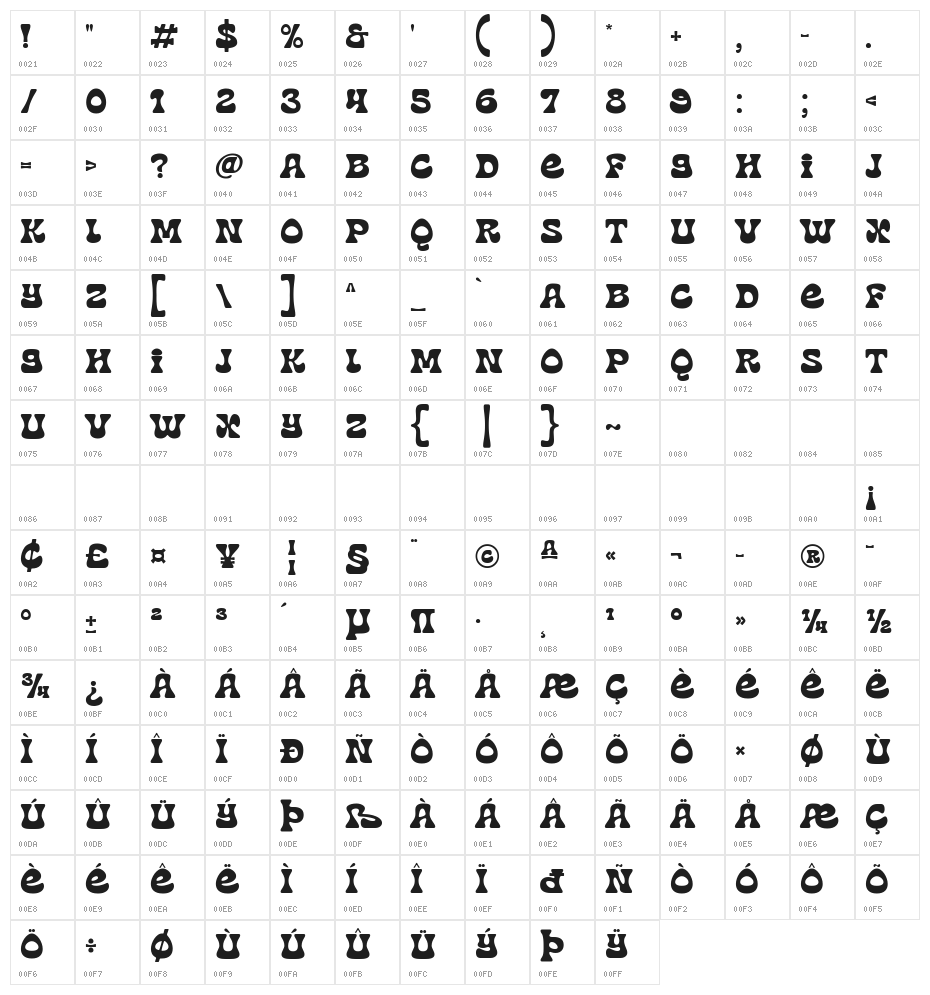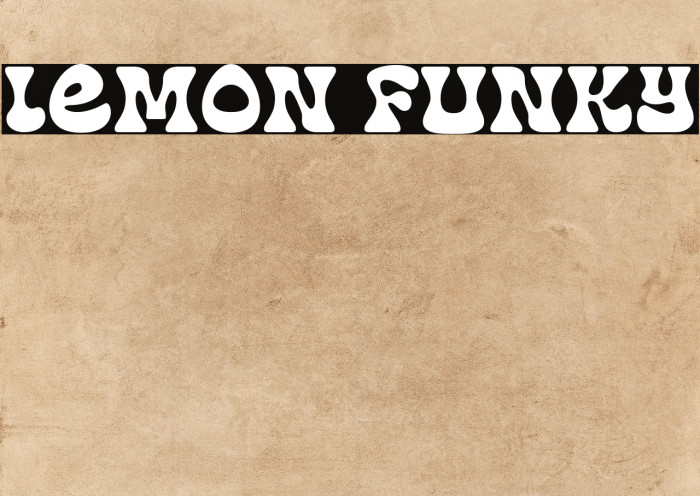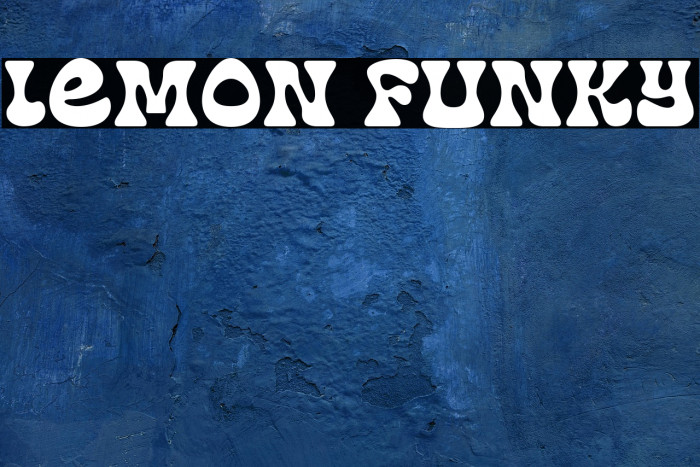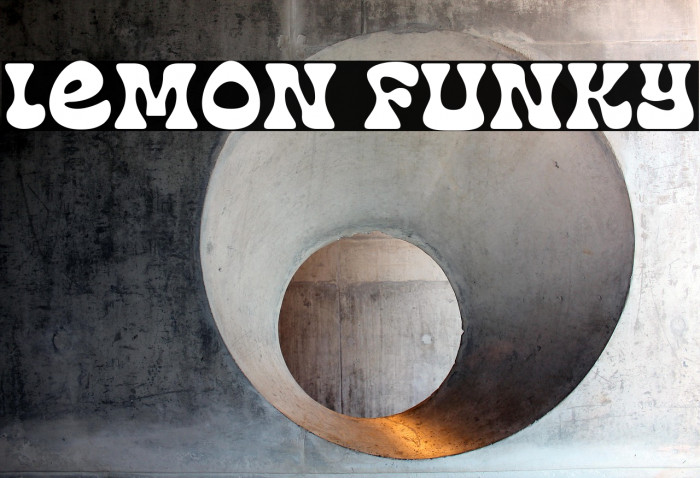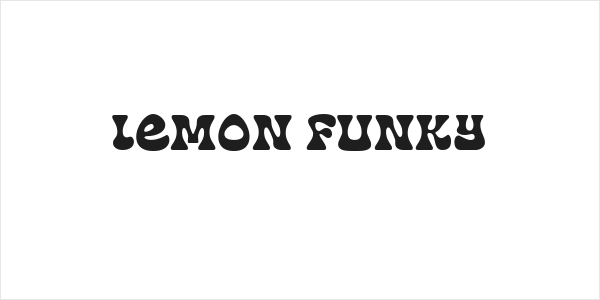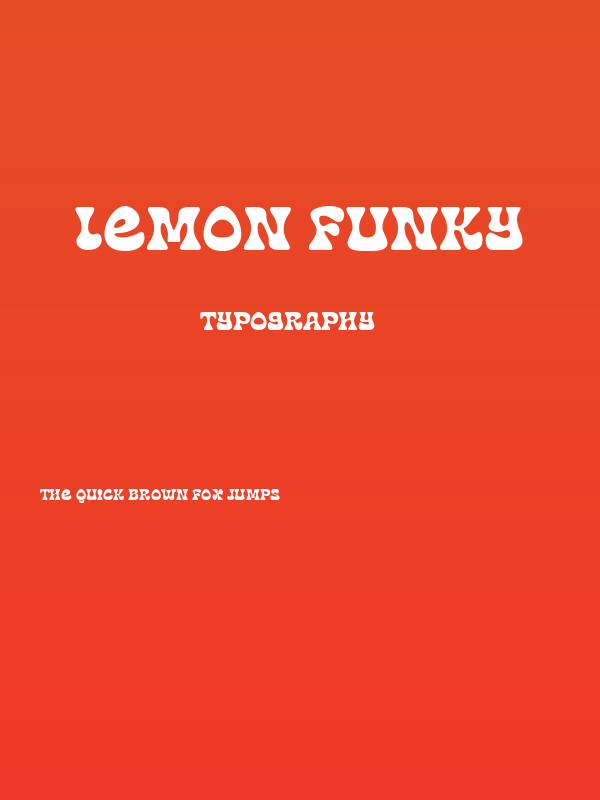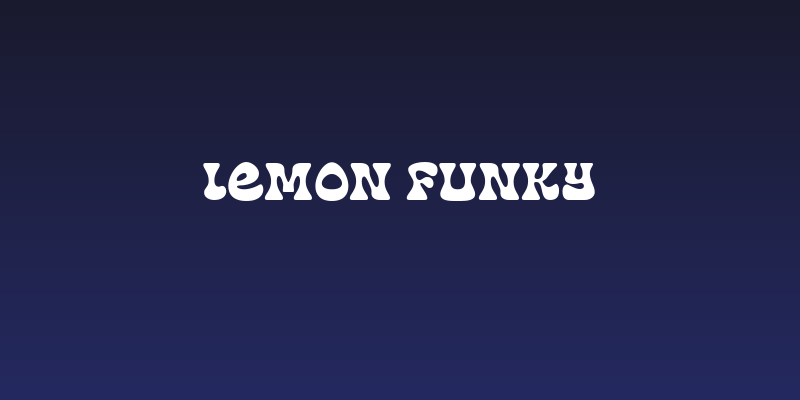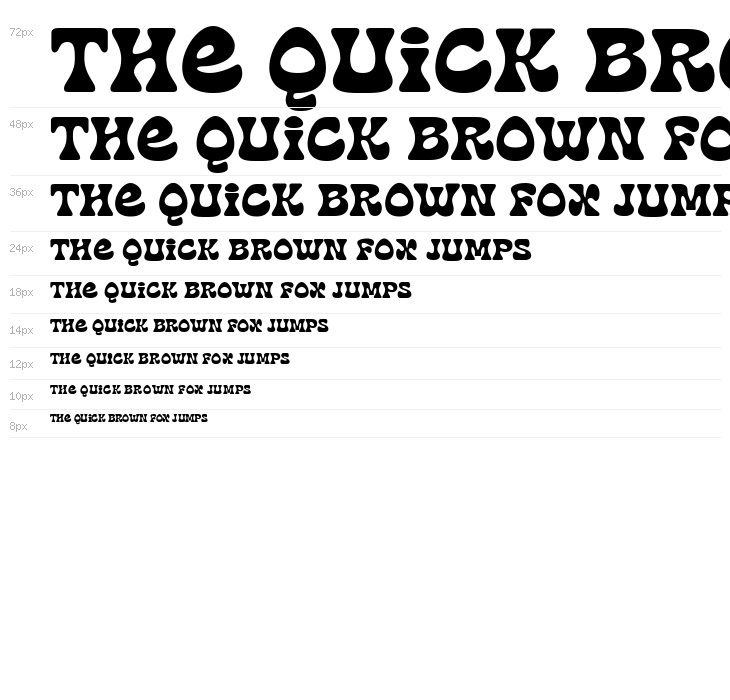
Lemon Funky Font
| Stile generale | Playful, Whimsical |
| Progetti proposti | Ideal for children's books, playful branding, party invitations, and creative posters. |